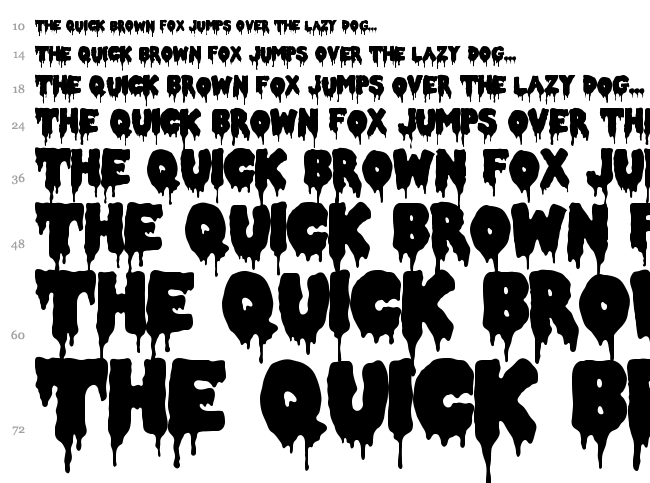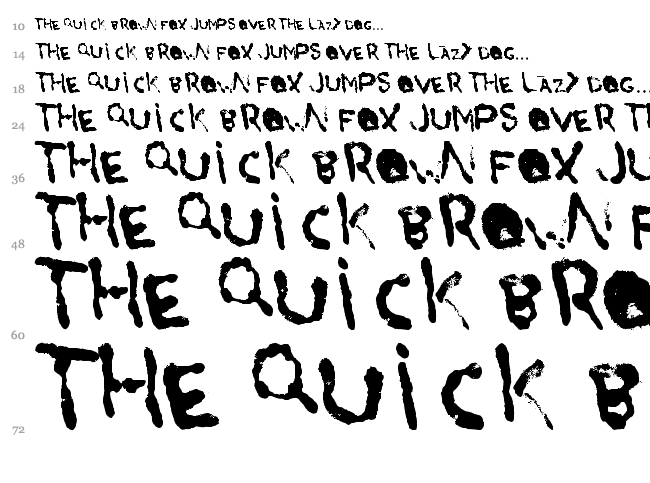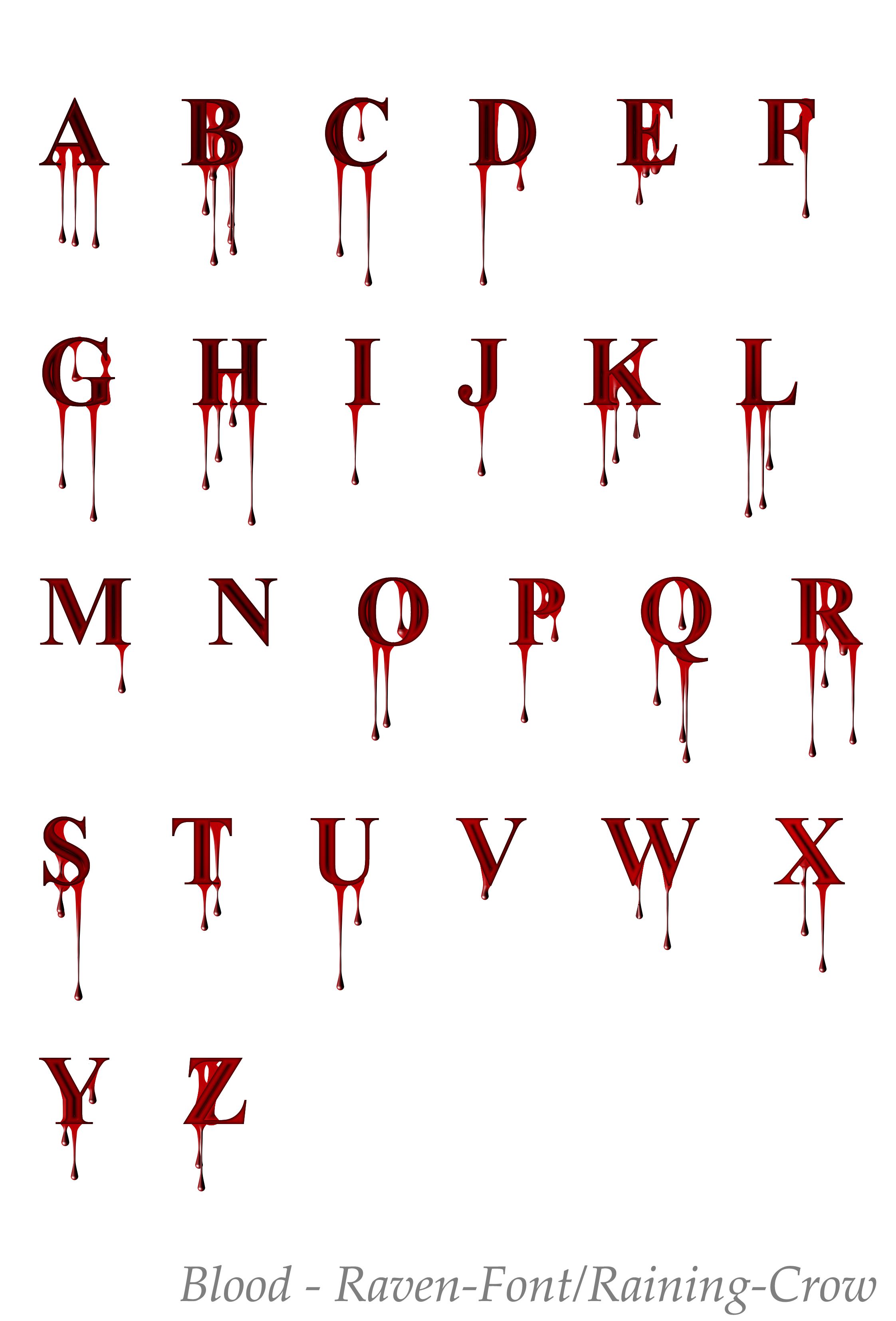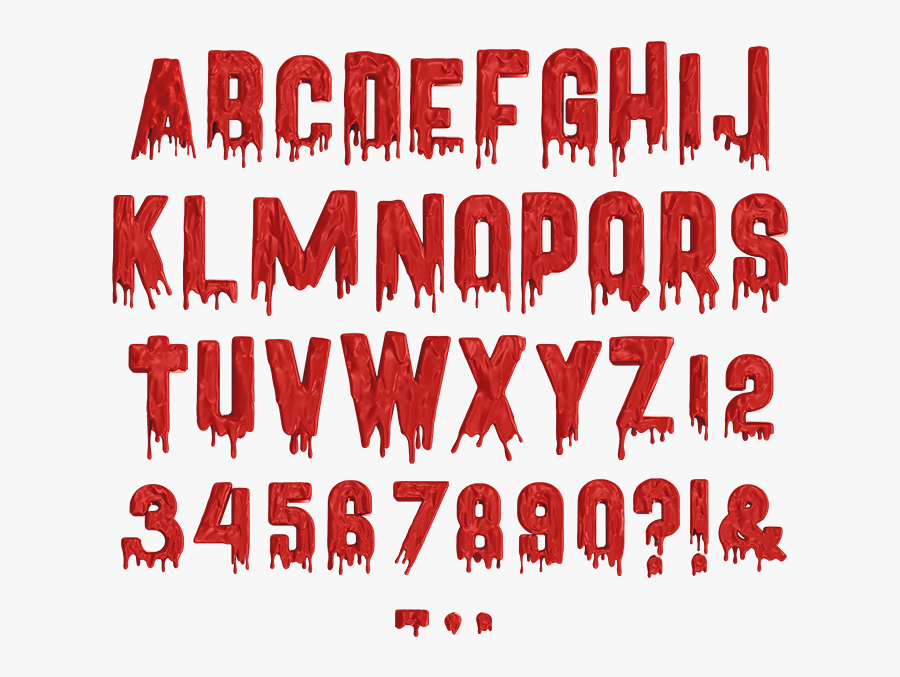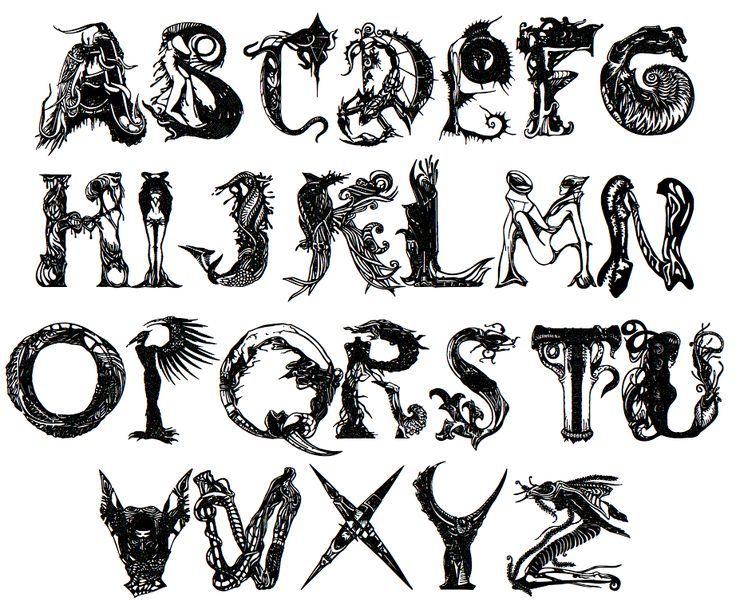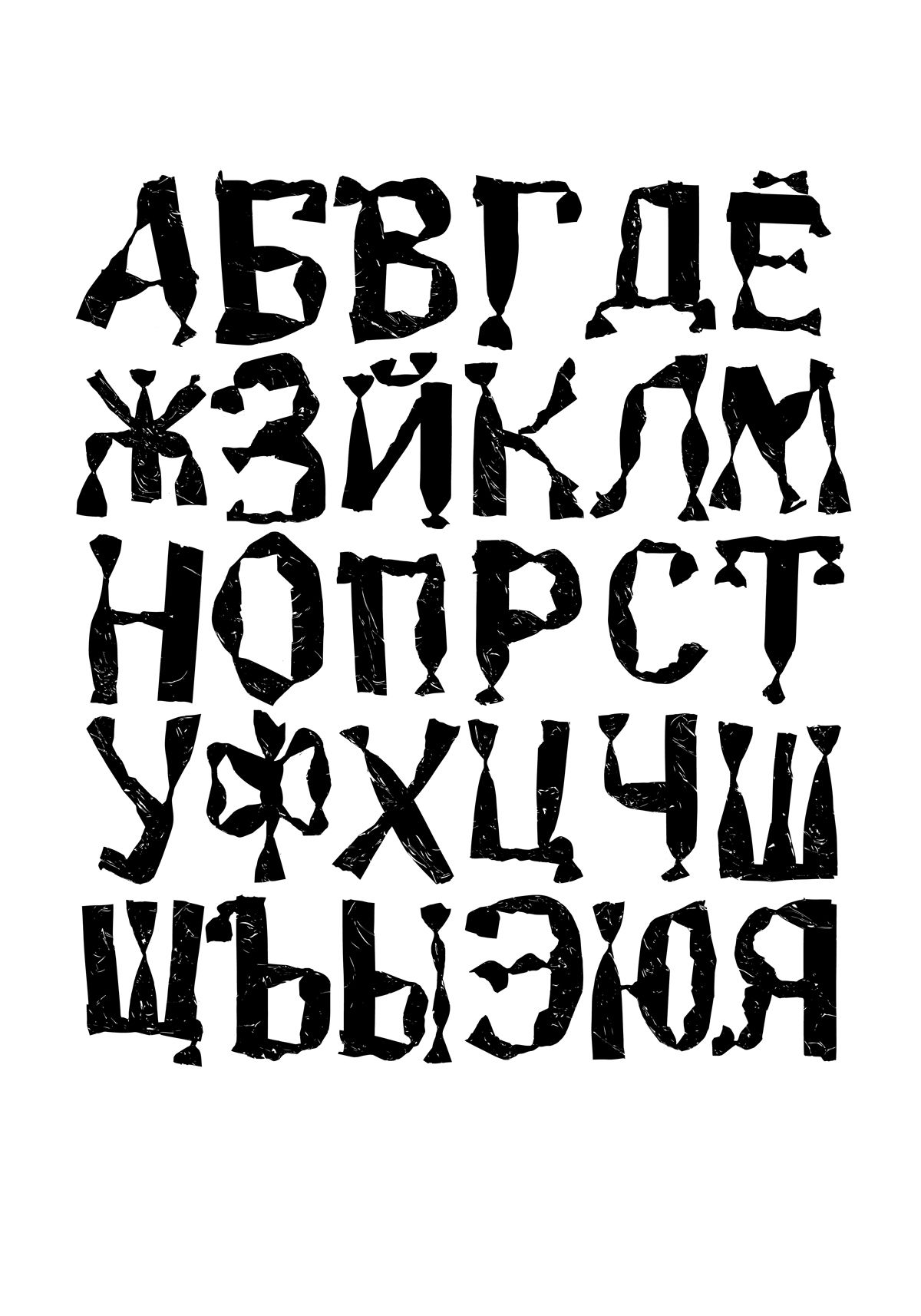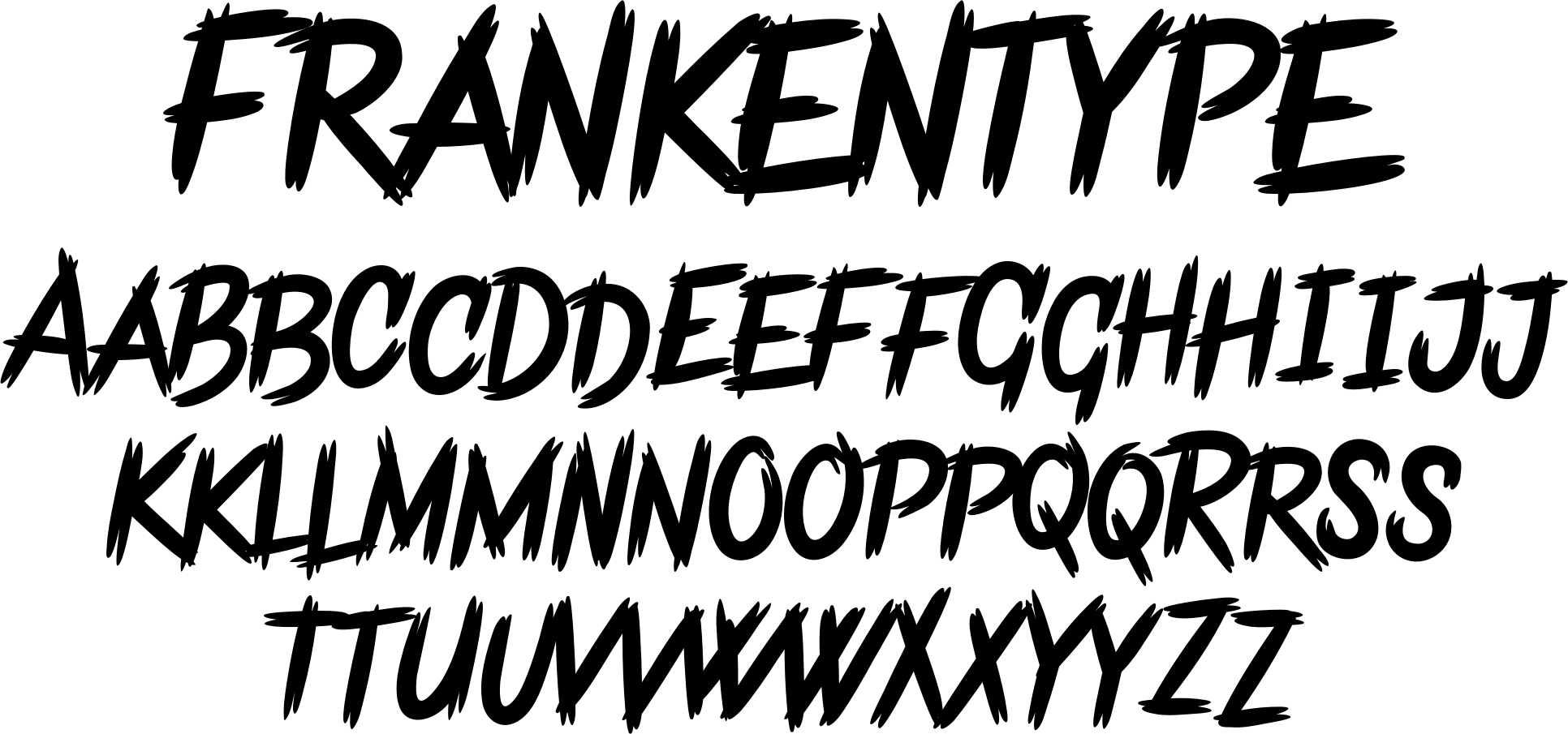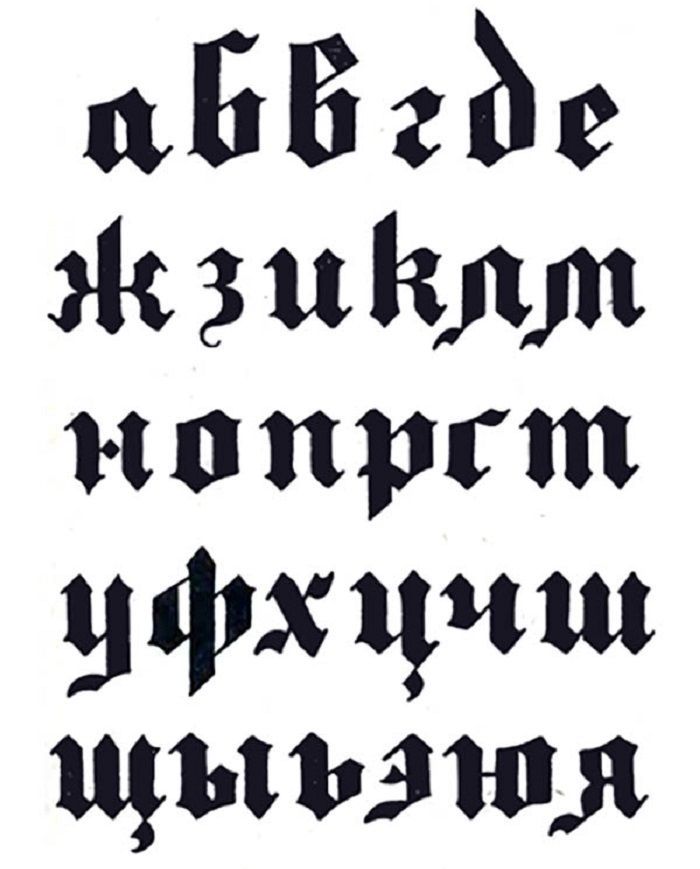
55+ лучших страшных хэллоуин шрифтов для Фотошопа
В мега-наборе всяческих материалов для хэллоуина иконок, фонов, вектора и т.п. мы публиковали в том числе и страшные шрифты для Фотошопа. Однако тогда это было лишь частью большой статьи, и должного внимания им уделить не получилось. Сегодня исправим эту ситуацию, т.к. в нашем распоряжении будет полноценная заметка.
По факту эта ниша больше всего схожа размытыми нечеткими и декоративными шрифтами и может содержать некоторые нестандартные элементы в буквах. Следовательно нужно грамотно подбирать фонты и использовать исключительно для подходящих нужд (когда это действительно обосновано) — поэтому применять ужасные шрифты в стиле хоррор для презентации квартального отчета на совете директоров — не лучшая идея;)
Nightmare 5
Blood Crow
DBE-Beryllium
You Murderer BB Font
The haine au carre
Amhole
Last N Line
Scary Halloween
Halloween Too
Blood Lust
Cocaine Sans
Bleeding Freaks
Something Strange
Curse of the Zombie
çarşı
Grim Ghost
crAZYSCARYhalLowEeN
Survival Horror
CF One Two Trees
Think Nothing
Чаще всего нам попадаются хоррор шрифты из ужасов и похожих фильмов или тематических оригинальных постеров, афиш, листоков — т.
е. полиграфии. В онлайне использовать их приходится куда реже — идеально подойдет мрачным готическим порталам/сайтам. Иногда они встречаются в рассылках или онлнай иллюстрациях, например, по поводу запуска скидок ко Дню всех святых или в приглашениях на готическую вечеринку.
Psychotic
Nemo Nightmares
Ghoulish Fright AOE
Riky Vampdator
Raven Song
Blasphemy
Phantom Fingers
Face Your Fears
DZR MENTAL
Gypsy Curse
Black Widow
The Defiler
Blood Seeker
A Lolita Scorned
Horroroid Staggered
Blood Thirst
Crucifixion
HEADHUNTER
Cold Night for Alligators
Manhunter
Lakeshore Drive
No Fear
Butcher the Baker
Burn The Witch
Who asks Satan
the Gingerbread House
Hellion
Bates Shower
Freakshow
Tarentula’s Web
Как и в ситуации со шрифтами мелом на доске специфика применения материалов играет большую роль.
Halloween Hand drawn Creepy Font Alphabet
Red Creepy Horror Font on Black
Halloween Blood or Paint Splatters
White Ghostly Fonts
Horror Film Typesetting
Scary Style Letters
White Horror Font